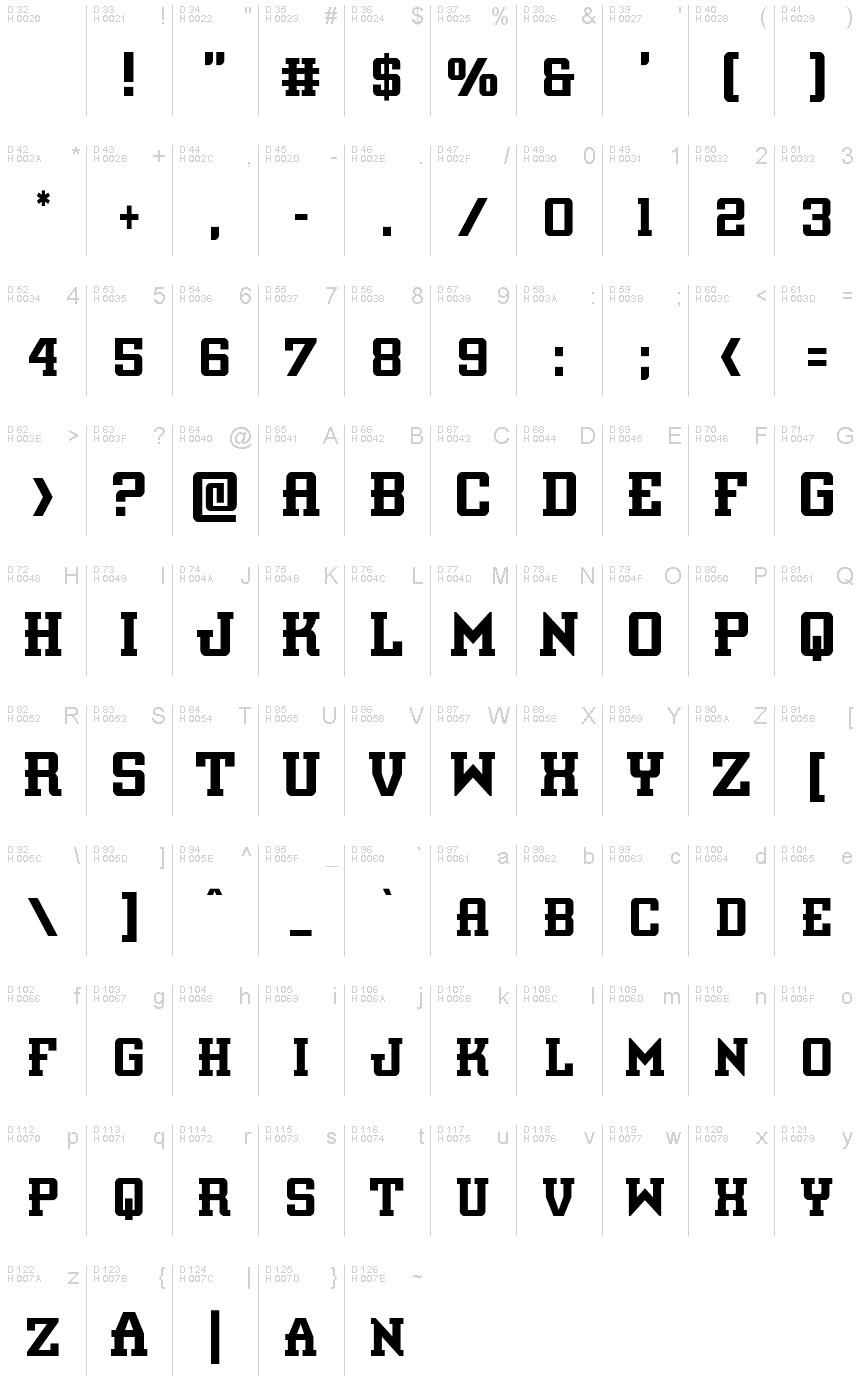
Interceptor Condensed von Iconian Fonts ist eine kostenlose Techno-Display-Schrift mit einer markanten, retro-futuristischen Ausstrahlung. Die Großbuchstaben basieren auf blockartigen Vertikalen und breiten Slab-Serifen, doch die abgerundeten Außenkanten verhindern, dass die Buchstaben zu starr wirken – was der Schrift einen stromlinienförmigen Charakter verleiht, wie man ihn von Typenschildern kennt.
Sie eignet sich hervorragend für Poster, Spiele-Logos, Titelkarten, Sci-Fi-Verpackungen und auffällige Überschriften, wenn ein kompakter Headline-Stil mit „Machine-Age“-Attitüde gefragt ist, ohne dabei direkt wie ein Stencil-Font zu wirken. Da es sich um eine kostenlose Schrift handelt, ist sie auch ideal für Monogramme, Team-Logos und kompakte Branding-Elemente, da die Buchstaben selbst in kurzen Wörtern konstruiert und ausdrucksstark wirken.